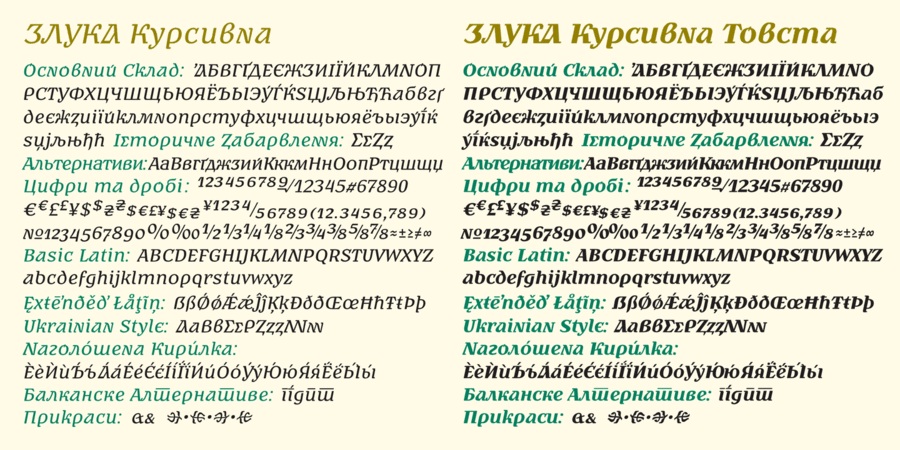
Zluka (6 шрифтів)
Гарнітура Злука зроблена за мотивами літерації Петра Холодного, який, вочевидь спирався на доробок Георгія Нарбута та Марка Кірнарського, що започаткували виразний, але трагічно перерваний разом з історією Української Республіки, стиль українського шрифту. Пропонований проект є повноцінною складальною гарнітурою у 6 накресленнях. Шрифт названо на честь знаменної для України події – Злуки Західньої Української Народньої Республіки та Української Народньої Республіки в єдину незалежну Українську Народню Республіку, 22 січня 1919 року. Гарнітура містить сучасну слов’янську кирилицю з можливостями наголосу та сучасну європейську латинку, історичні та стилістичні альтернативи, македонсько-сербський курсив, деякі декоративні елементи тощо. Злука призначена для широкого кола завдань: від логотипу та фірмового стилю до суцільного тексту в газетах, часописах, книжках та на вебсайтах відповідного змісту. Шрифт розробили Геннадій Заречнюк та Віктор Харик за участю Сергія Ткаченка у 2018 році.